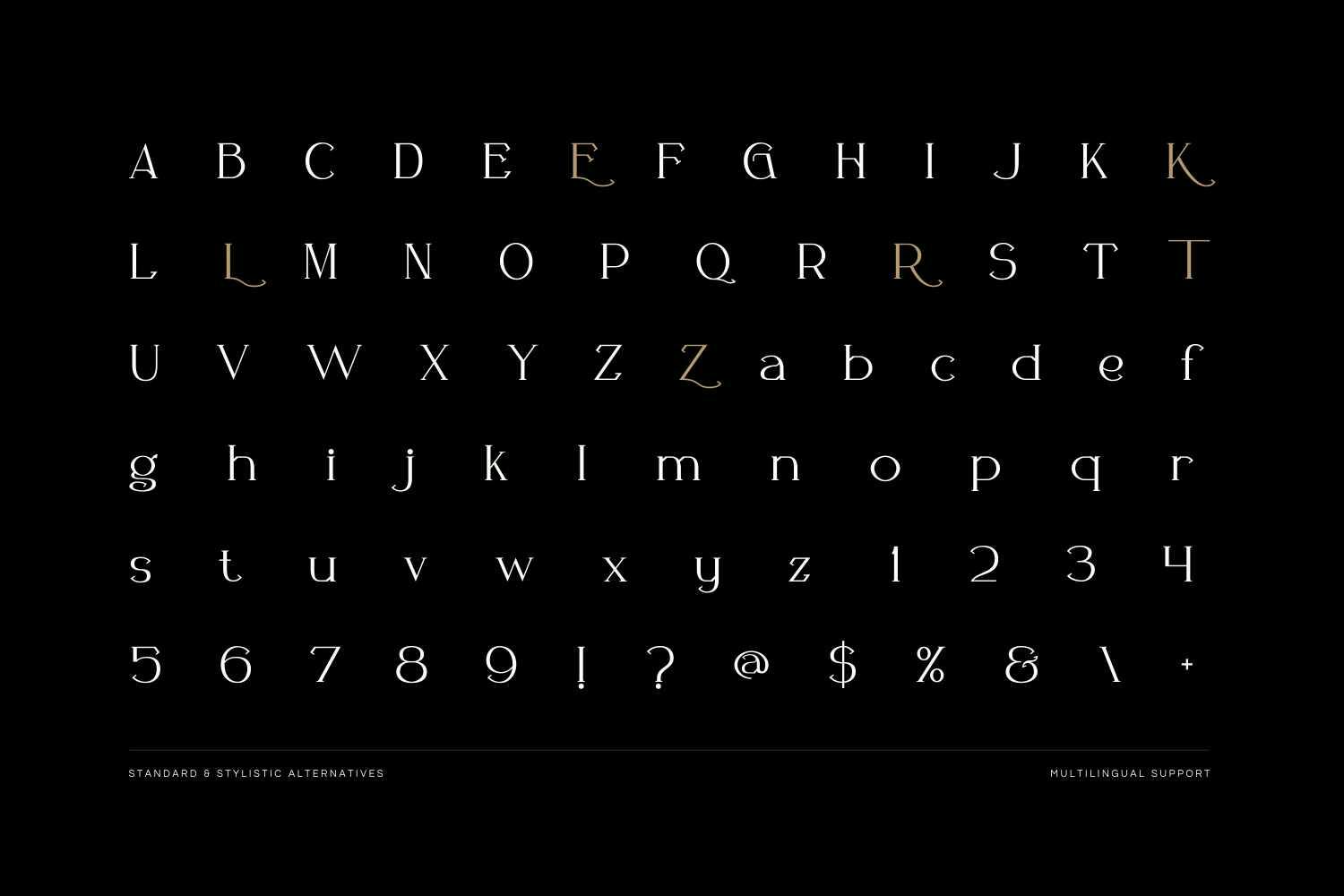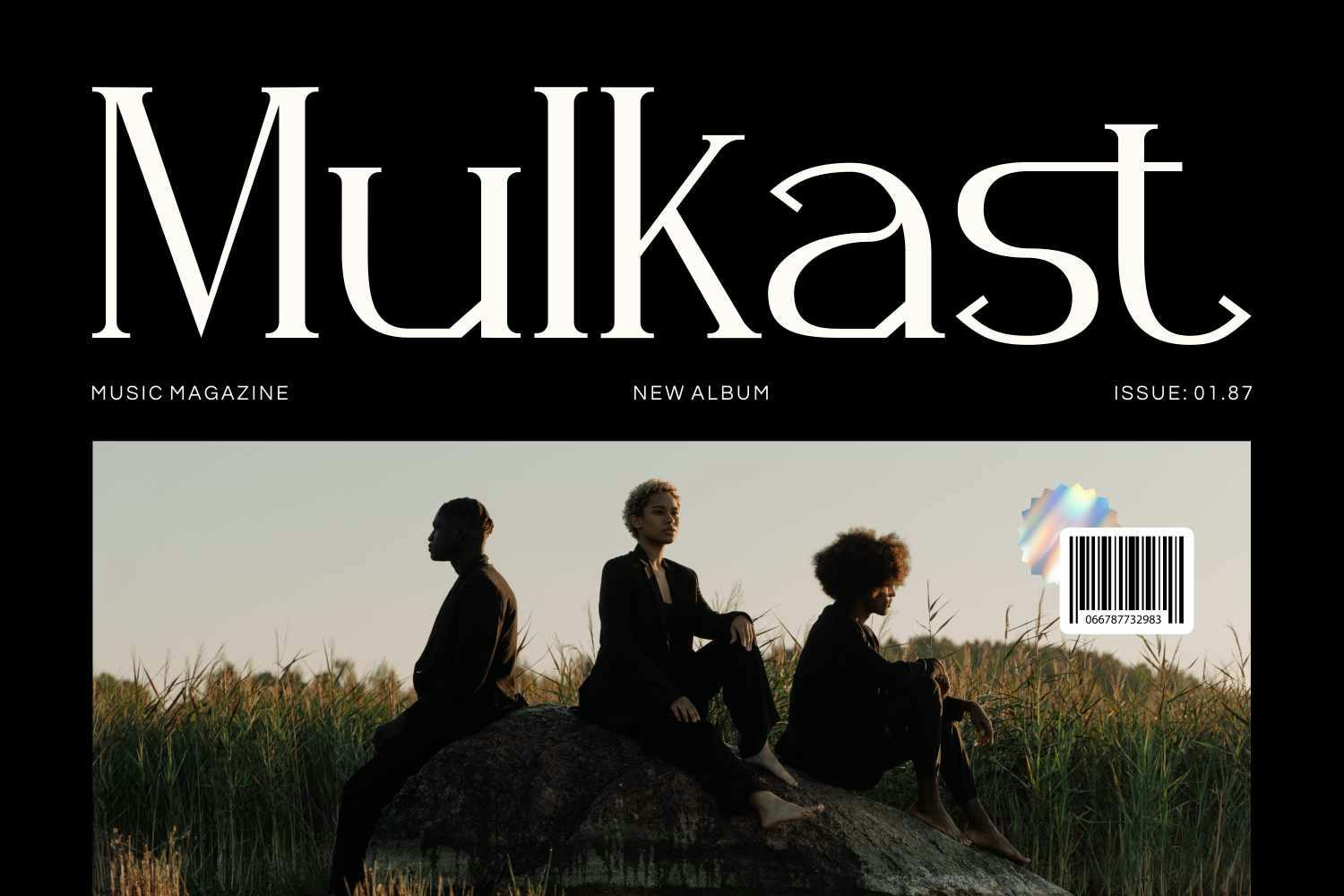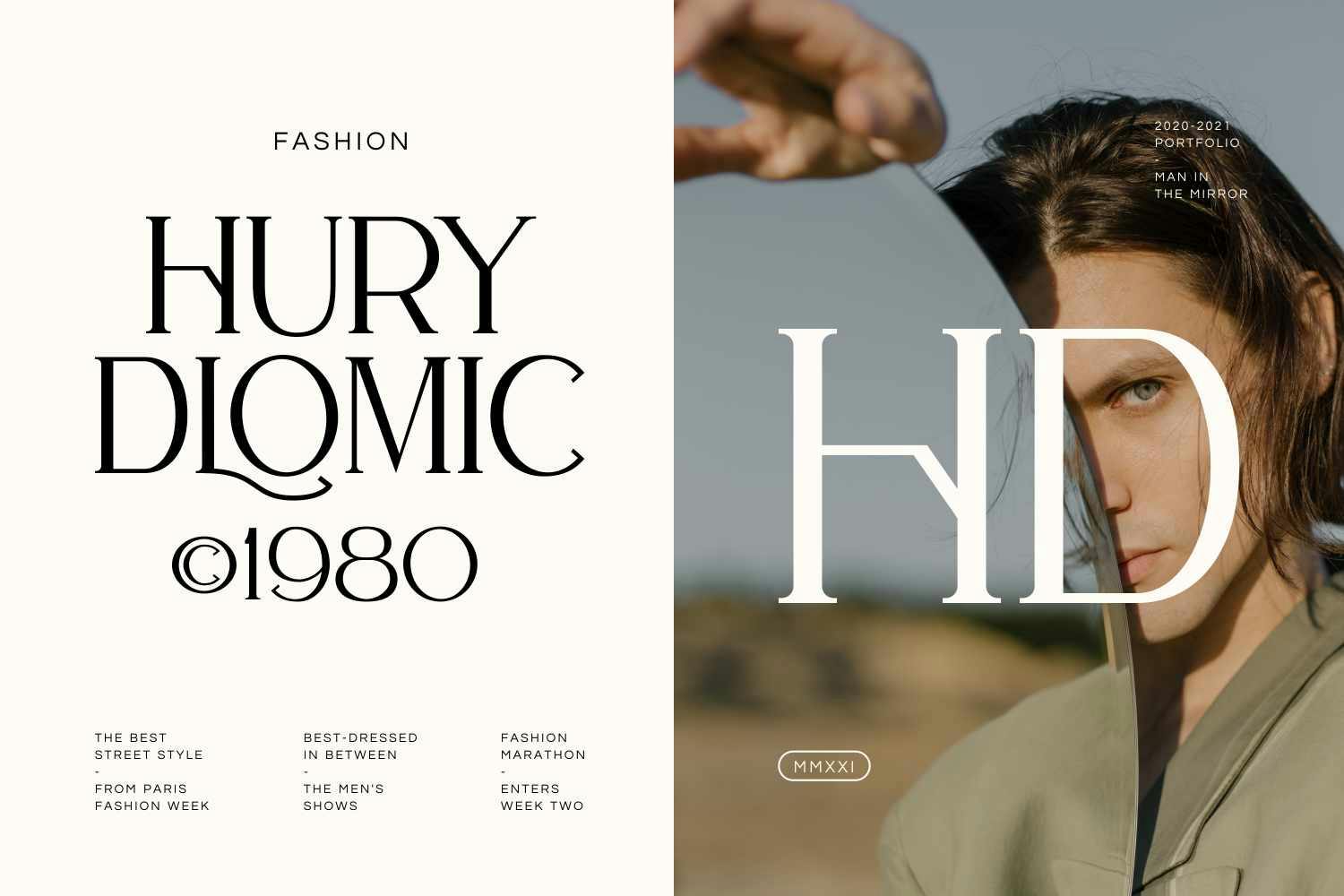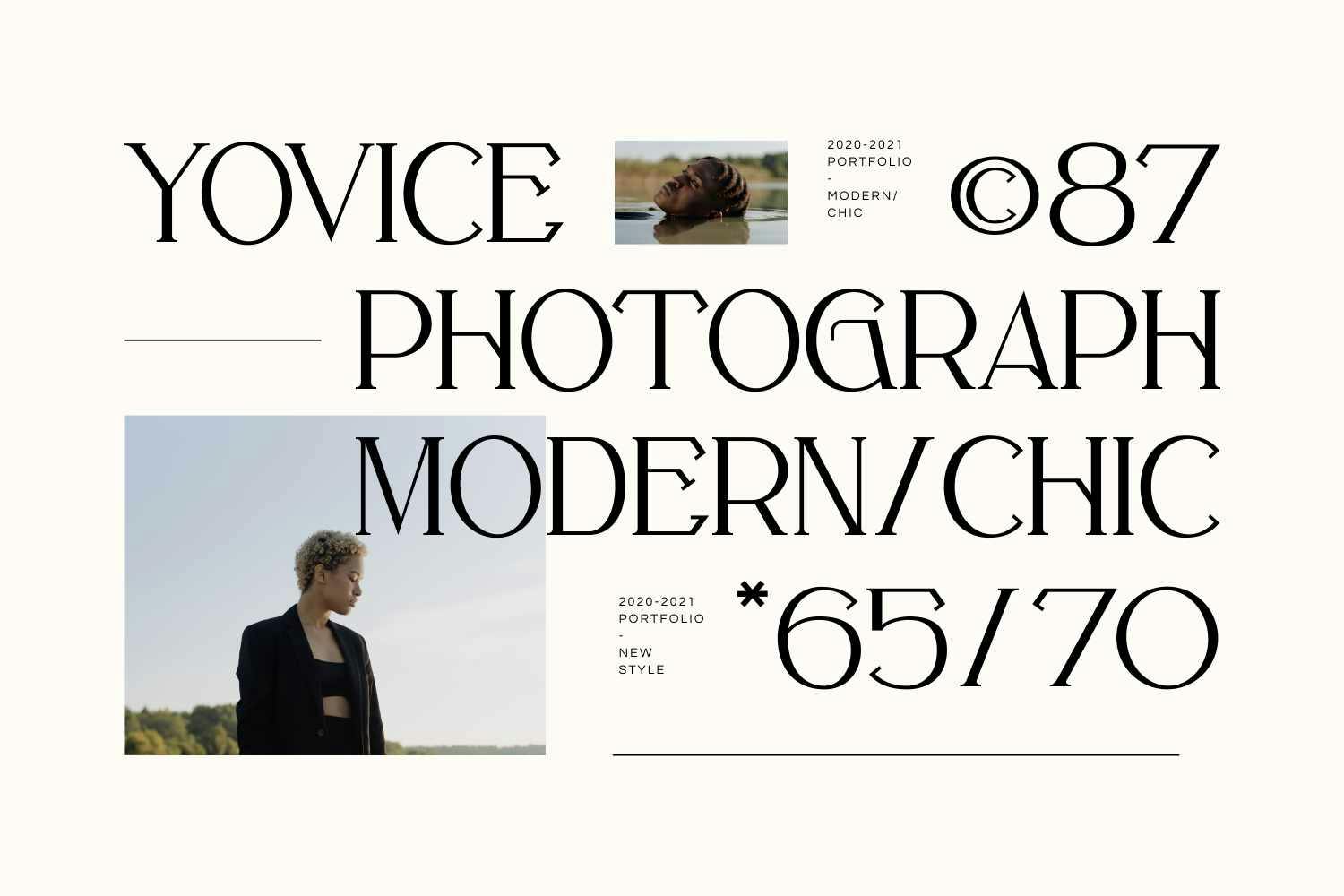
محصول فونت Gnore برای بسیاری از پروژههای شما مانند طراحی لوگو و برندینگ، عکاسی، دعوتنامهها، واترمارکها، تبلیغات، طراحی محصولات، لوازمالتحریر، طراحیهای عروسی، برچسبها، بستهبندی محصولات، رویدادهای خاص و بسیاری دیگر مناسب است.